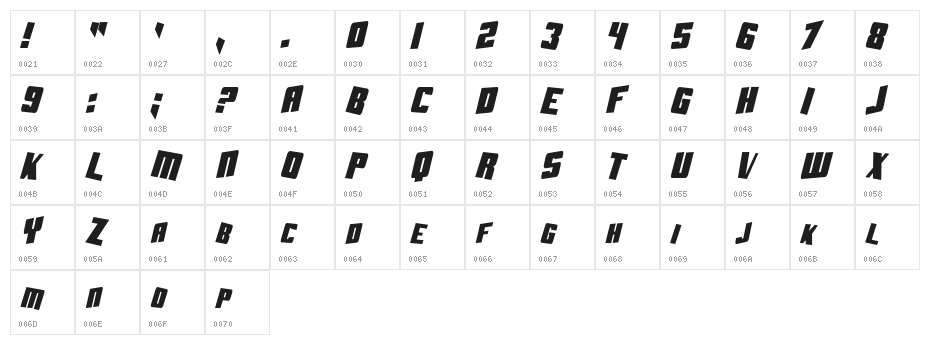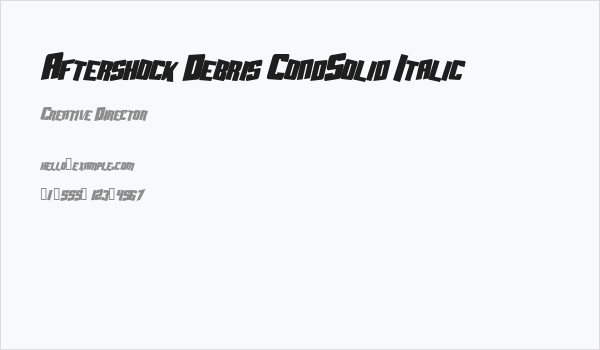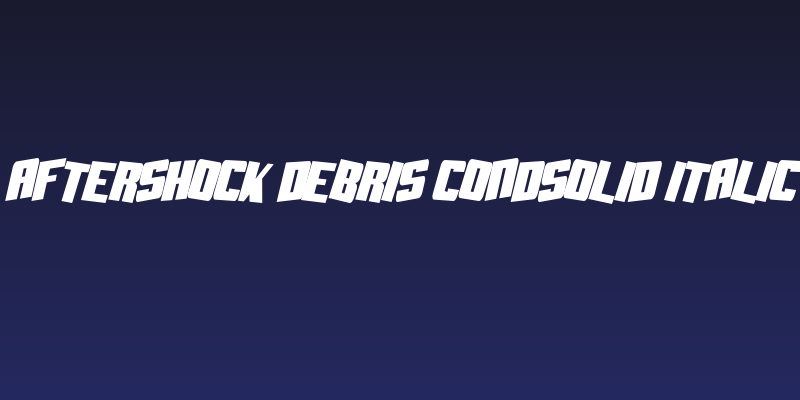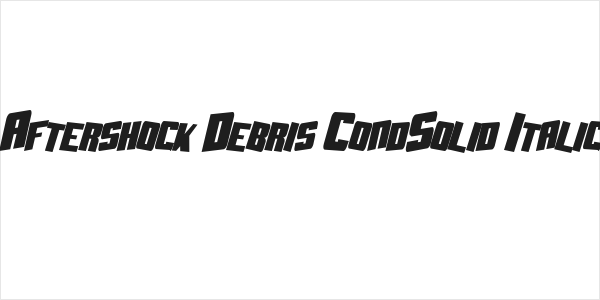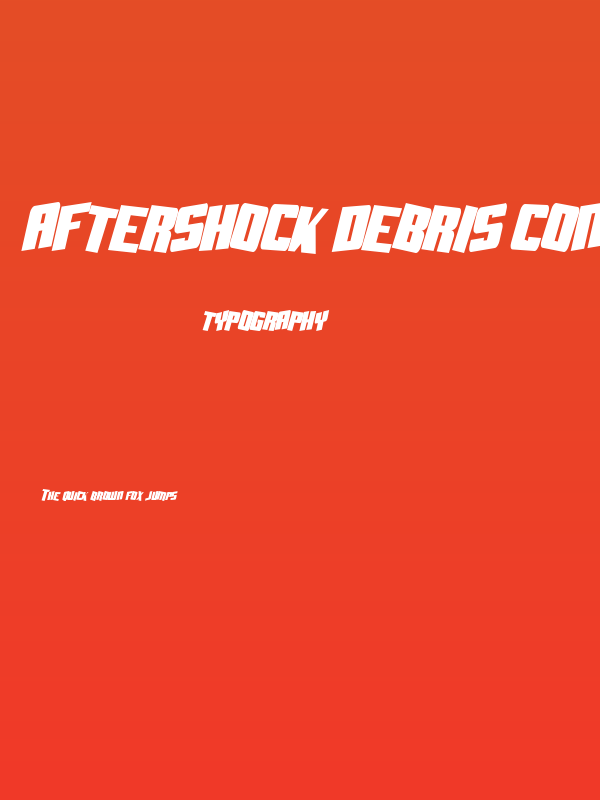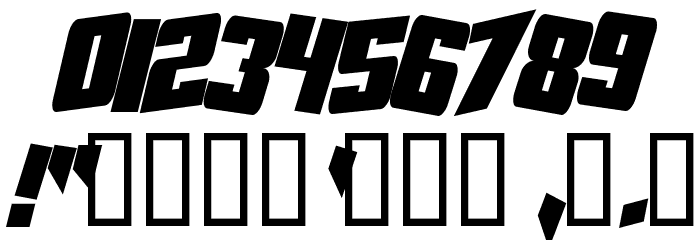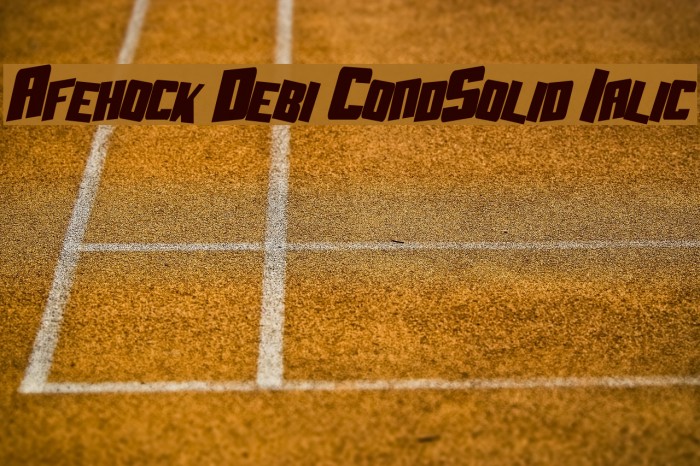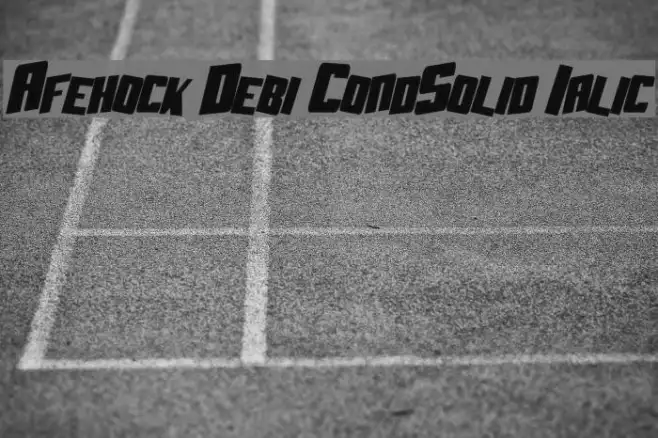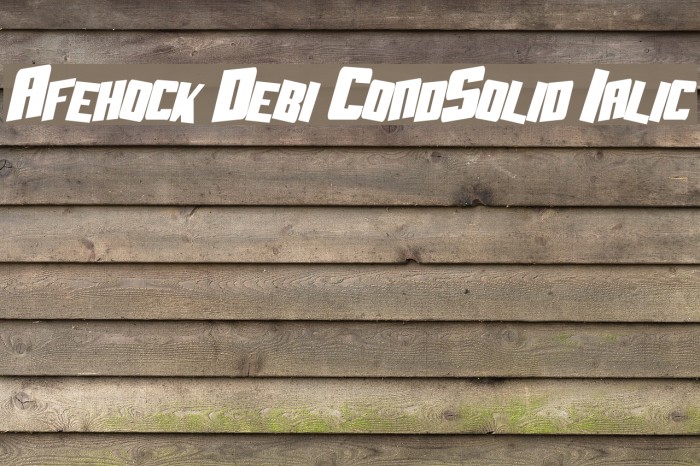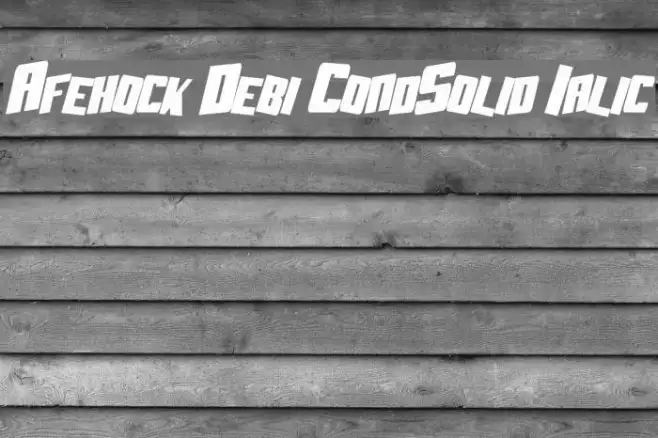
Aftershock Debris CondSolid Italic Font
| Projets proposés | Ideal for sports branding, action movie posters, video game titles, and dynamic advertisements. |